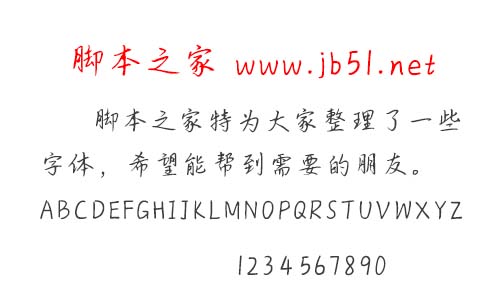
漢儀一顰一笑都是你字體是漢儀字庫推出的一款手寫風(fēng)格藝術(shù)字體,字體筆觸較為粗實,具有很好的視覺效果,適合應(yīng)用于藝術(shù)設(shè)計、平面宣傳設(shè)計、網(wǎng)頁設(shè)計,書法字帖等領(lǐng)域,歡迎喜歡漢儀一顰一笑都是你字體的朋友前來下載使用。